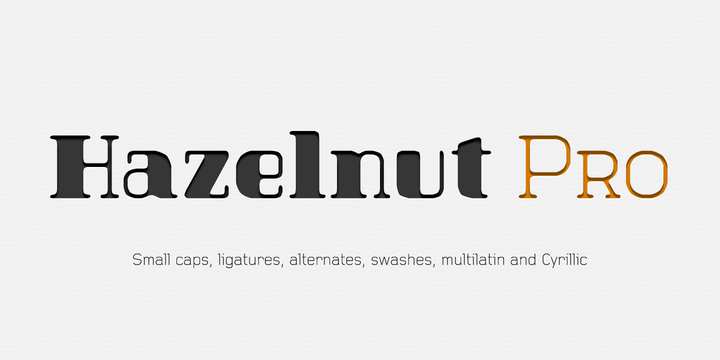
A ‘Hazelnut Pro Font Family’ é uma delicada proposta de fontes display que traz um charme único e elegante para qualquer projeto editorial ou tipográfico. Com apenas quatro tipos de letra, esta família atende a diversas necessidades sem comprometer sua estética minimalista e sofisticada. O maior destaque da ‘Hazelnut Pro’ é o seu recurso interessante: ambas as tonalidades incluem pequenos caps em seus conjuntos de alternativas estilo tipográfico. Além disso, oferece um formato desenhado e trabalhoso para cada uma das letras do alfabeto que adiciona um toque adicional à sua identidade visual. Para designers apaixonados por fontes minimalistas ou aqueles buscando aperfeiçoamento em seus projetos tipográficos, ‘Hazelnut Pro’ é o complemento perfeito. Seu design suave e moderno combina com uma ampla variedade de estilos e se adaptará ao seu trabalho para criar um impacto imediatamente visível. Com a opção de usar conjuntos alternativos especiais e sua forma estilizada, você terá o poder de transformar qualquer layout em um design memorável e atraente. O ‘Hazelnut Pro’ foi criado pela Hamilton para designers que valorizam tanto a funcionalidade quanto a beleza de uma fonte elegante.